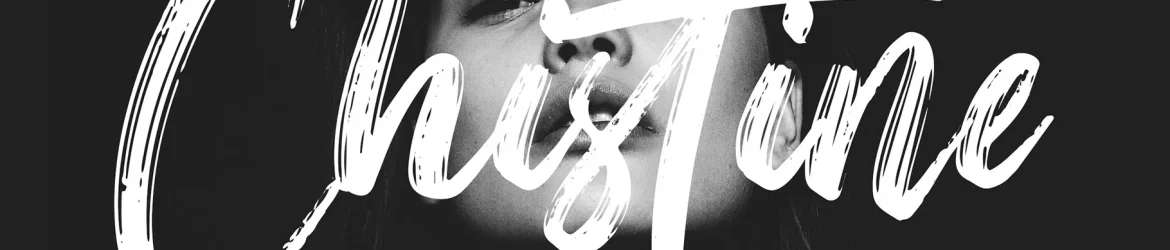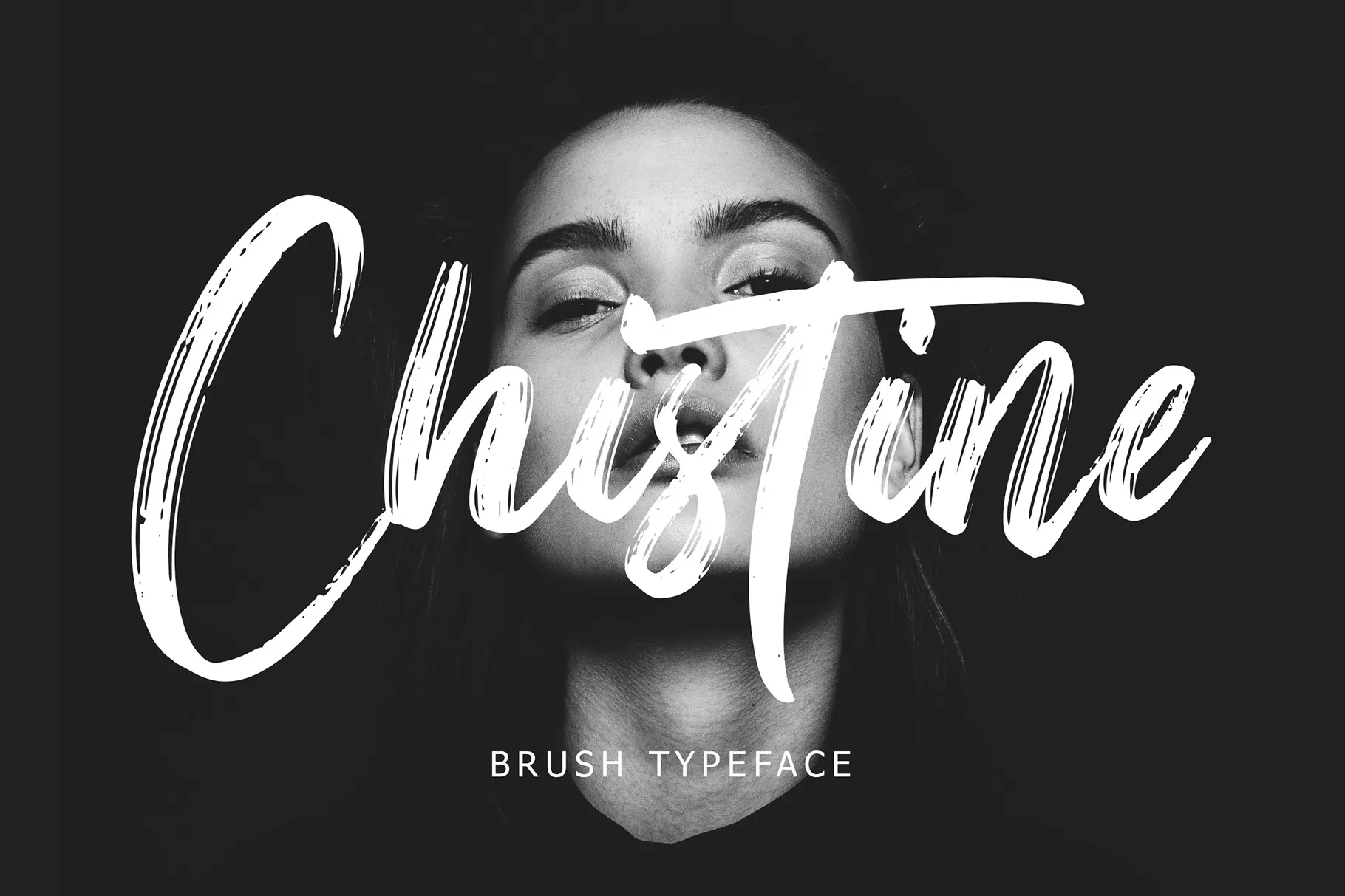
Christine Font
Christine é uma nova paleta de fontes modernas feitas à mão que traz estilo e versatilidade para qualquer projeto design. Criada pelo Studio Formatika, Christine se adapta perfeitamente a diversos estilos de designs, sendo especialmente adequada para trabalhos de marcação, logos, designs para casamentos, postagens no mídia social, anúncios, embalagens de produtos, desenho de camisetas, design de produto, rótulos, fotografia e até mesmo como fundo d’água. Christine é uma escolha ótima para qualquer projeto em que seja necessário um toque moderno e pessoalizado. Com seu design moderno e adaptável a várias necessidades, Christine pode ser o elemento perfeito para tornar seus projetos design ainda mais memoráveis.